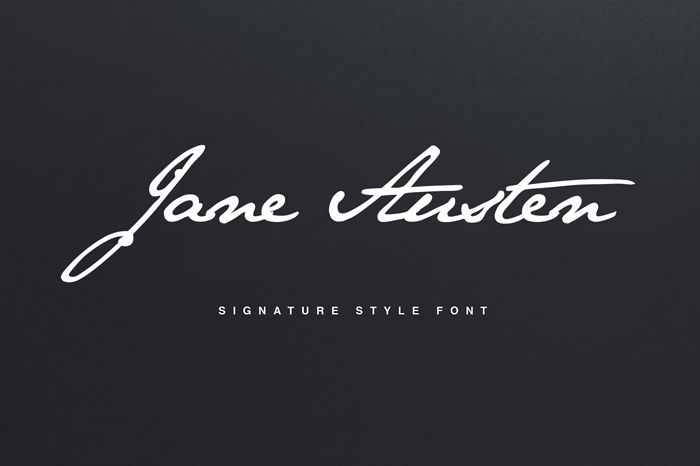
Jane Austen Signature Font – Download Grátis
Estamos muito felizes em apresentar Jane Austen Font para você, uma impressionante obra de escrita manuscrita que combina elegância com autenticidade única. Jane Austen foi criada e compartilhada pelo designer pia-frauss e é um estilo de firma natural e autêntico, inspirado na letra da literária Jane Austen. Esta fonte é perfeitamente adequada para aplicativos diversos como logotipos, etiquetas de nome, citações escritas a mão, embalagens de produtos, materiais de merchandising, redes sociais e cartões de felicitações. Ela contém um conjunto completo de letras maiúsculas e minúsculas, uma ampla variedade de pontuação, números, e suporte multilíngue. Jane Austen é perfeita para aqueles que valorizam a autenticidade da escrita manuscrita em seus projetos. É um item valioso não apenas por sua beleza estética, mas também pela sua capacidade de tornar qualquer projeto mais único e pessoal. Este é um antigo design, mas ainda assim é tão relevante para os amantes do texto à mão quanto os novos designs. Jane Austen Font está disponível em uma vasta gama de usos criativos, sendo o ideal para quem procura fontes manuscritas autênticas e elegantes. Seja para criar sua própria marca pessoal ou adicionar um toque único a qualquer design que você deseje produzir, Jane Austen Font é uma escolha excepcional.